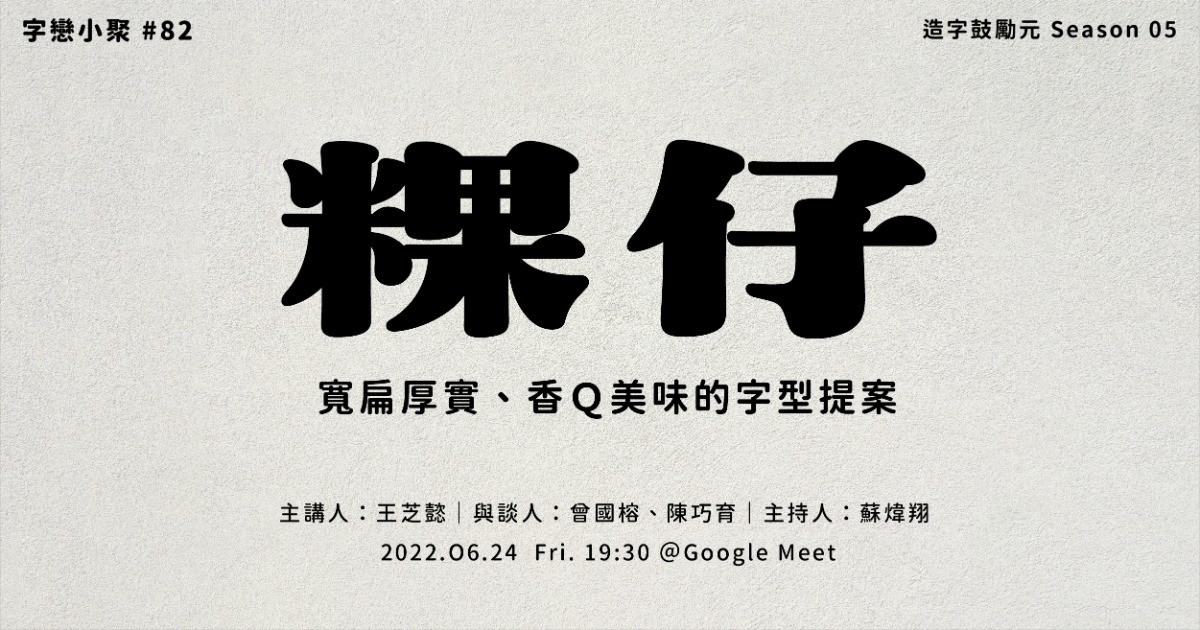
首獎得主王芝懿以「肥肉體」的提案進行輔導計畫。從一開始 5 個概念字樣,經歷六個月的時間,延伸到 200 個字。並且給予這個概念字型,新的命名:「粿仔」。粿仔是一套寬扁、厚實、溫潤的明體,以傳達食物的美味為訴求。芝懿將會分享她如何收斂筆畫造型、讓字體變得更有份量、讓字體更具有書寫韻味,以及如何逐步完成一套概念字型的提案成果。設計師的個性、喜好、生活經歷某種程度會反映在作品上,設計出「粿仔」究竟是什麼的個性的設計師與生活體驗?一起來聽聽看!
主講:王芝懿|第五屆造字鼓勵元首獎
與談:曾國榕、陳巧育、蘇煒翔